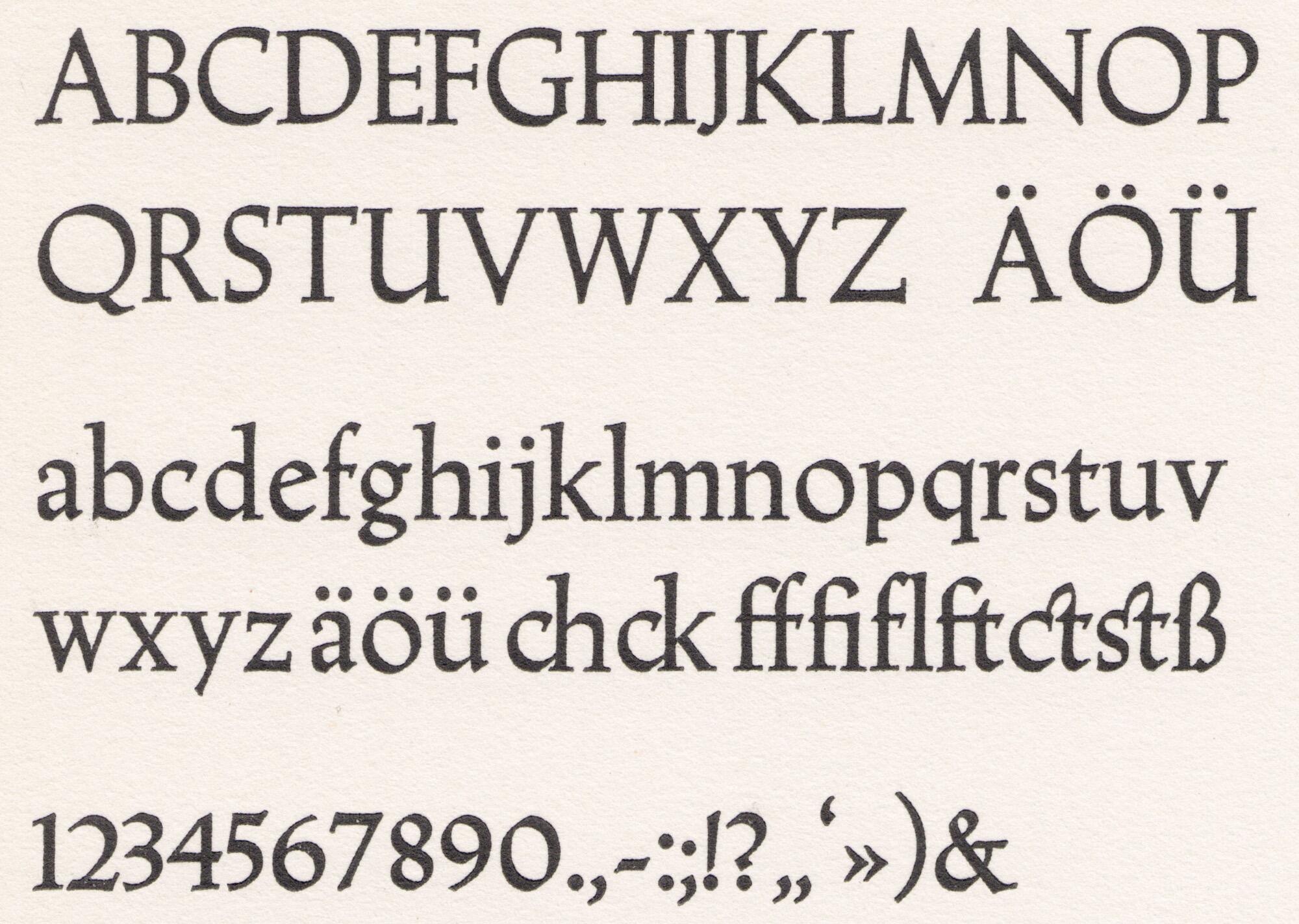
- 1939
- Antiqua humanistisch
Der US-amerikanischen Designers Warren Chappell benannte seine Schrift nach dem römischen Kaiser Trajan. Chappell wählte diesen Namen, da die Großbuchstaben seines Designs durch die Inschriften inspiriert wurden, die an der Trajansäule in Rom entdeckt wurden. Die Kleinbuchstaben zeigen dagegen den handgeschrieben wirkenden Breitfeder-Charakter früher Renaissance-Antiqua-Schriften.
Die Trajanus entstand in Zusammenarbeit mit der D. Stempel AG und erschien 1939 in einem aufrechten und einem kursiven Schnitt. Ein halbfetter Schnitt wurde 1940 nachgelegt. Heute ist die Schrift als Linotype Trajanus in drei Strichstärken erhältlich.